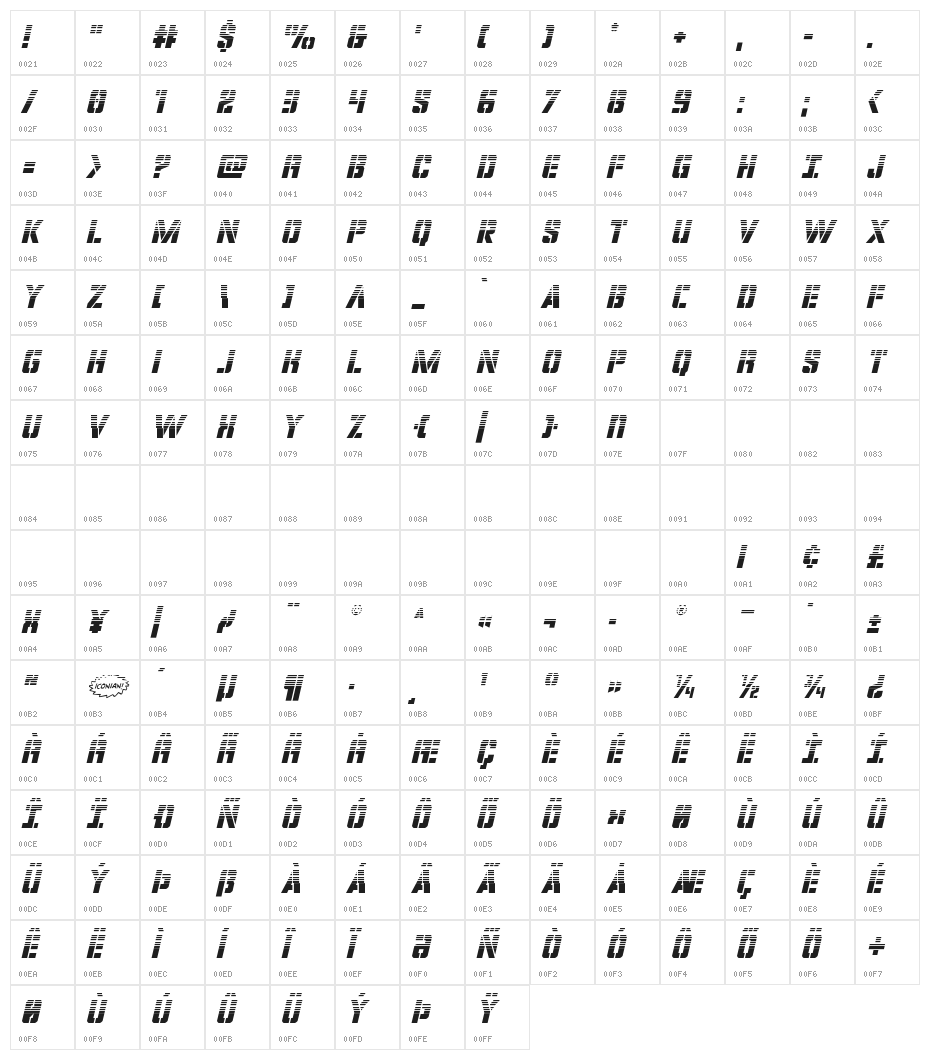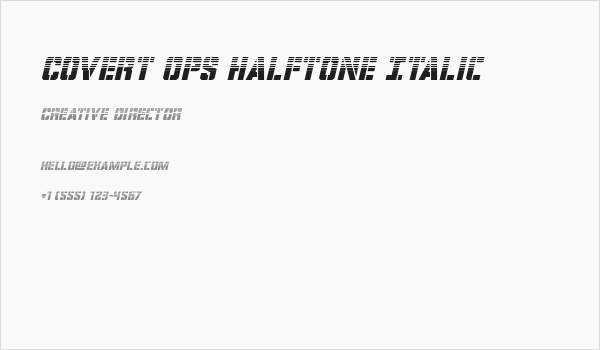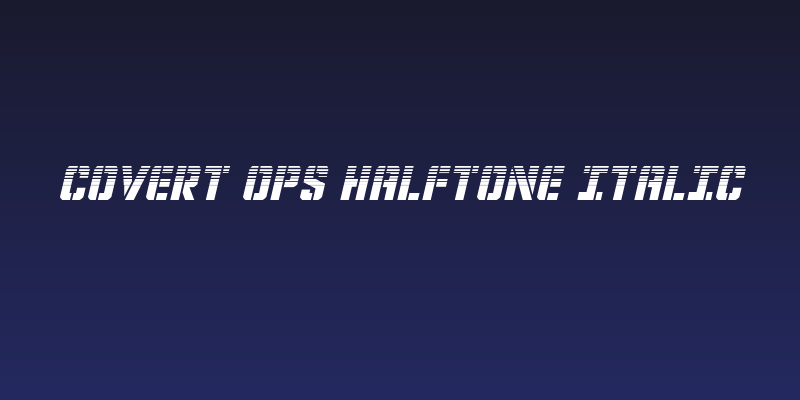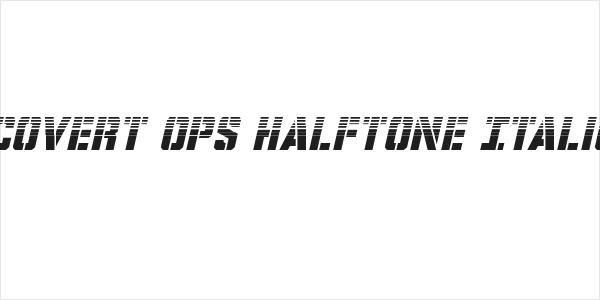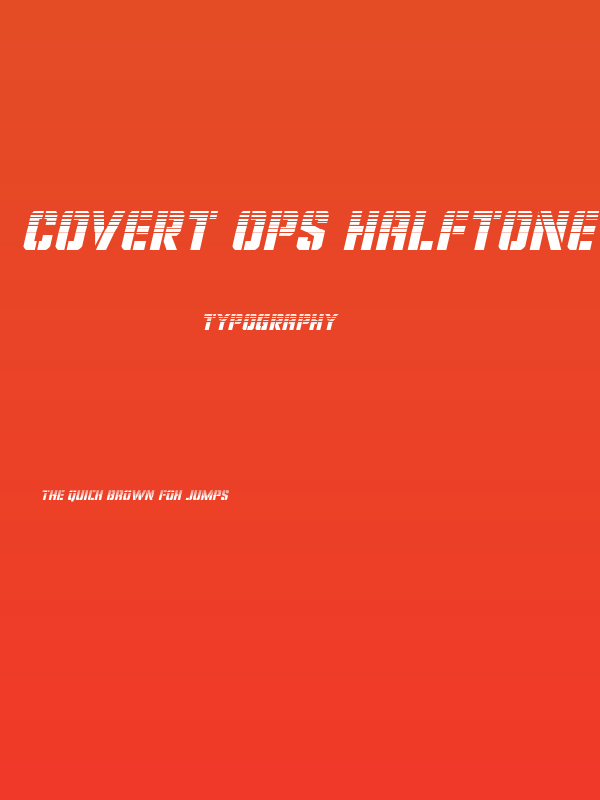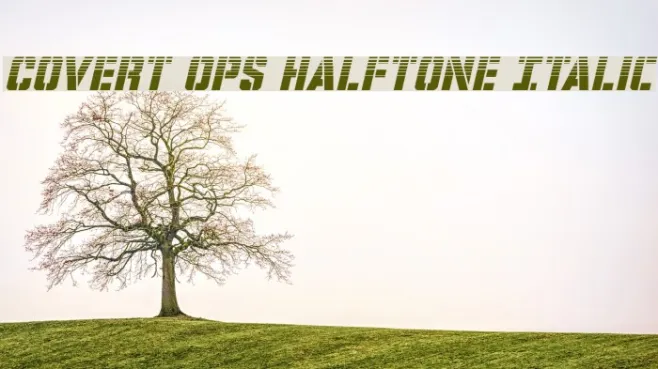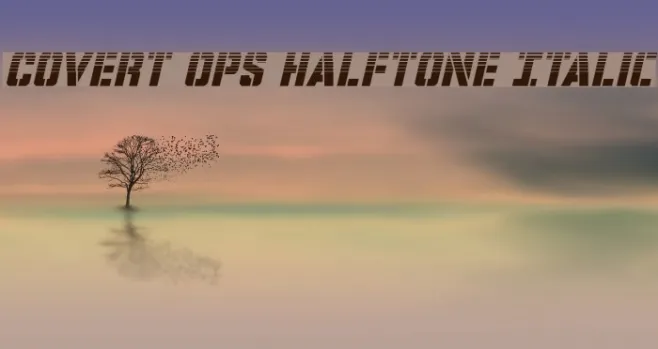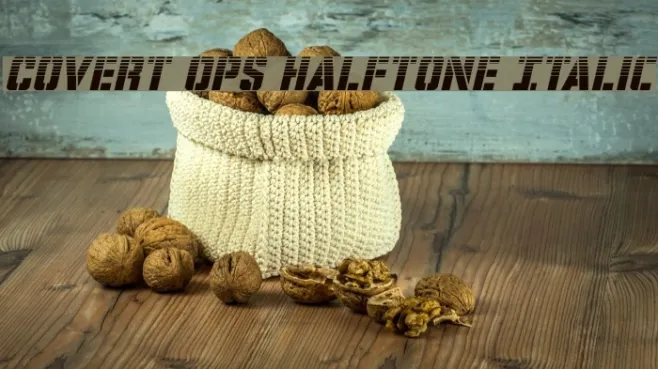
Covert Ops Halftone Italic Font
| Proyectos propuestos | Ideal for projects that require a futuristic or tech-oriented aesthetic, such as video game titles, movie posters, or branding for tech companies. |